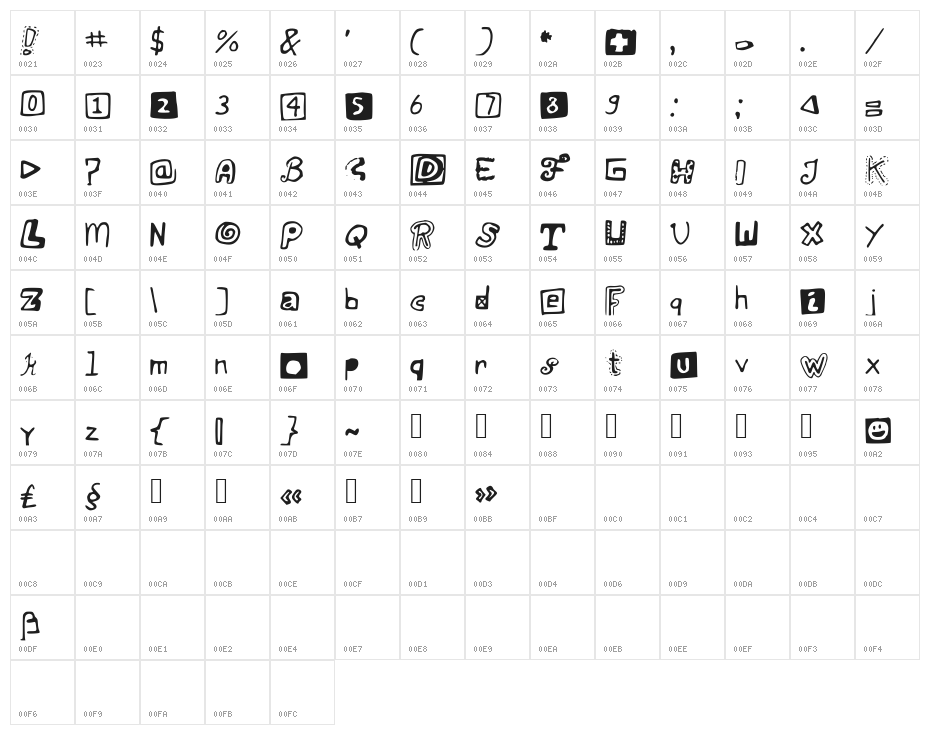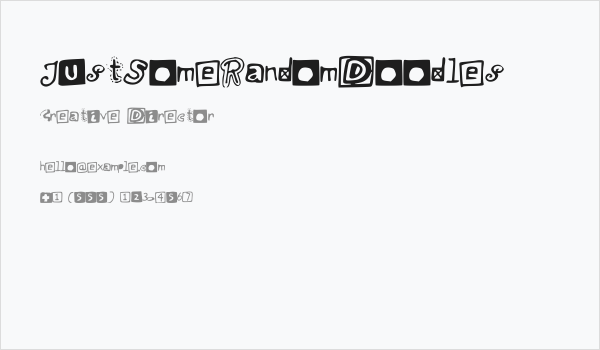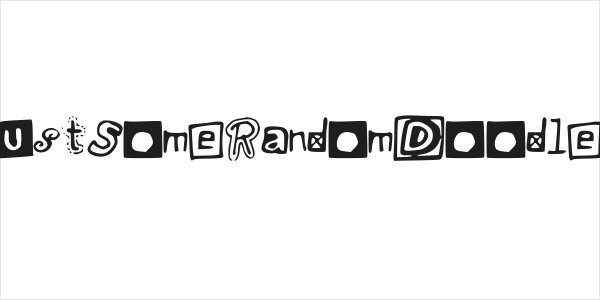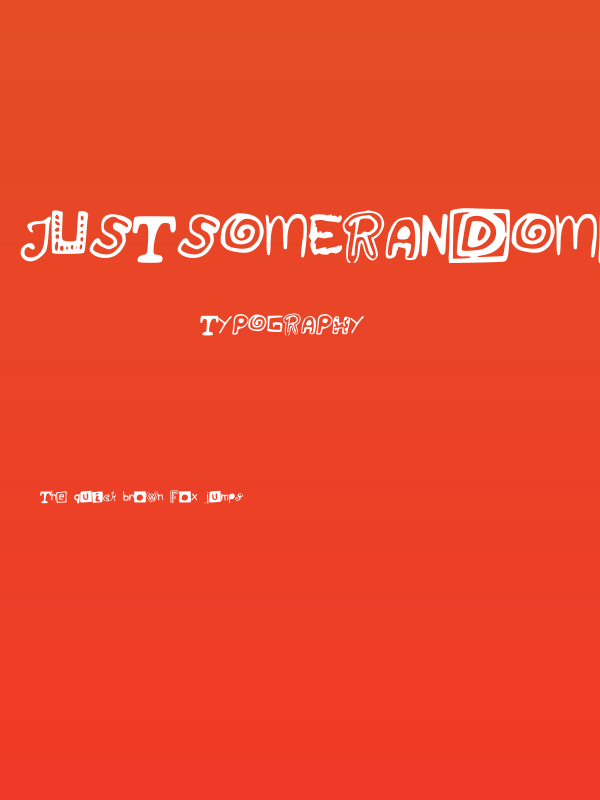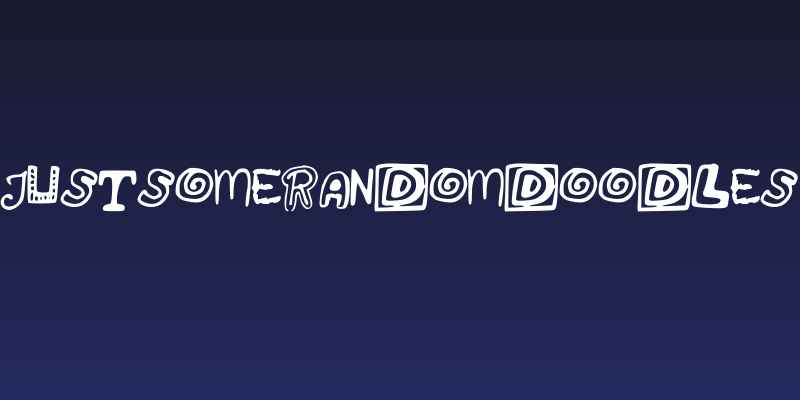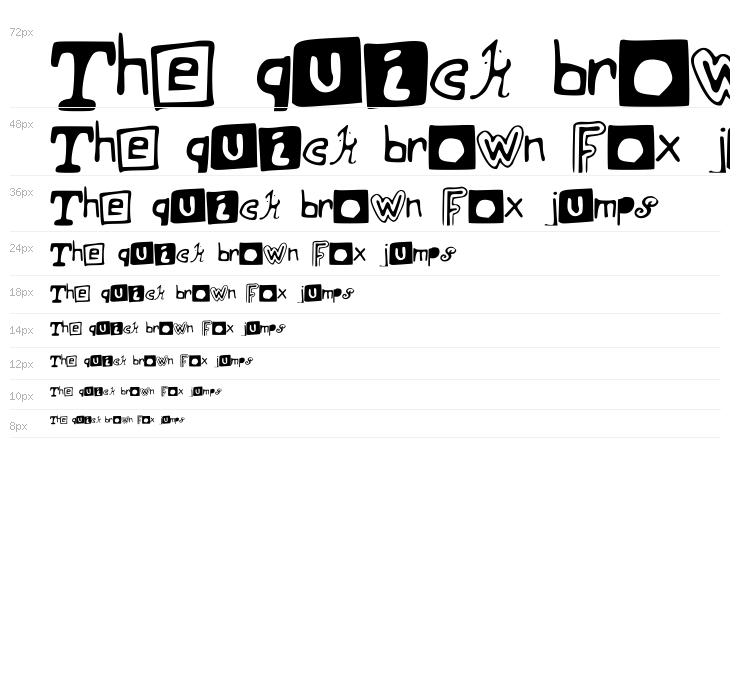
JustSomeRandomDoodles Font
| 推荐项目 | Ideal for children's book covers, playful posters, creative branding, and any project that requires a fun and lively typeface. |